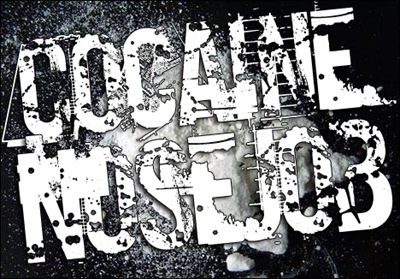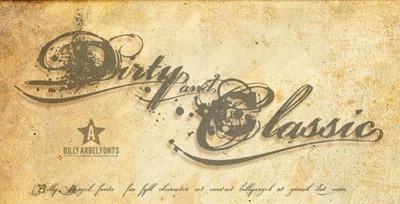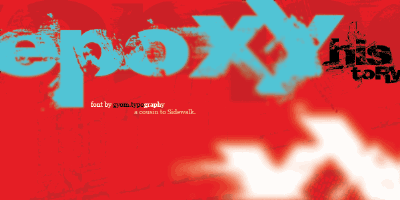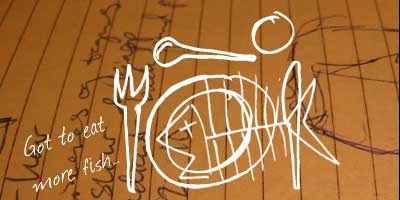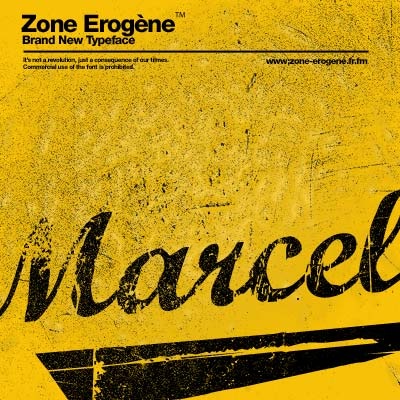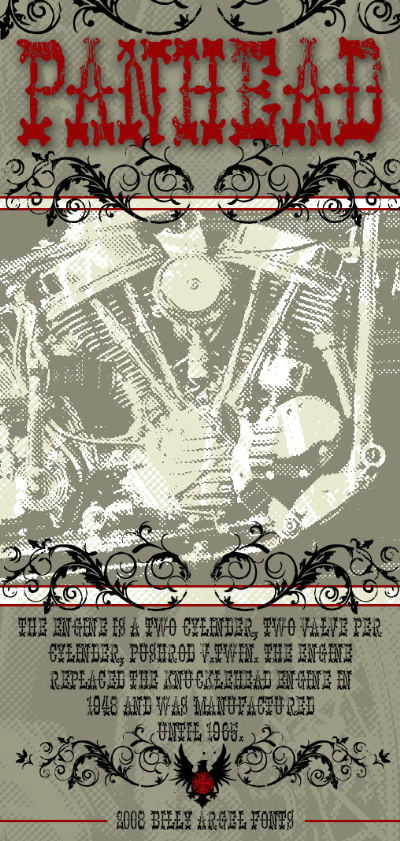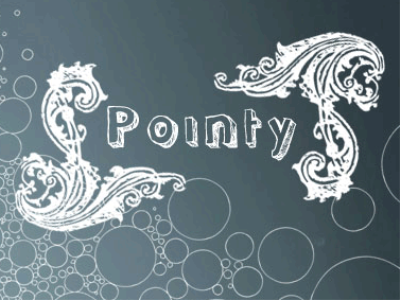
Стильные шрифты
Шрифт Cocaine Nosejob
Шрифт Dirty and Classic
классический гранжевый шрифт
Шрифт Epoxy History
шрифт в стиле гранж
Шрифт Hawaii Killer
ретро шрифт
Шрифт Jellyka Castles Queen
шрифт с завитками
Шрифт Journal
шрифт с рисунками
Шрифт Karabine
заштрихованный шрифт
Шрифт Marcelle
гранжевый шрифт
Шрифт Panhead
печатные шрифты
Шрифт Pointy